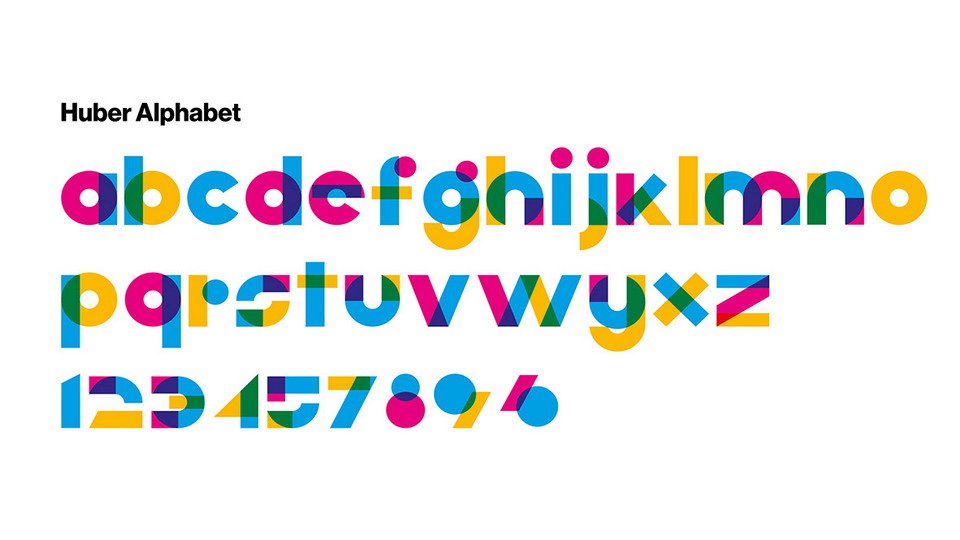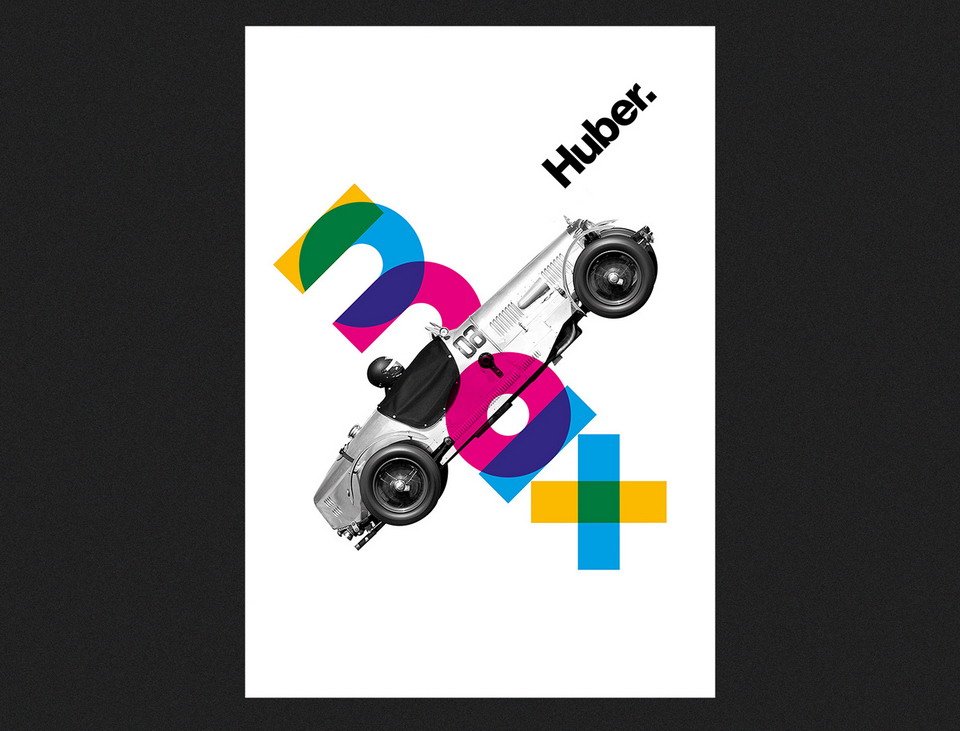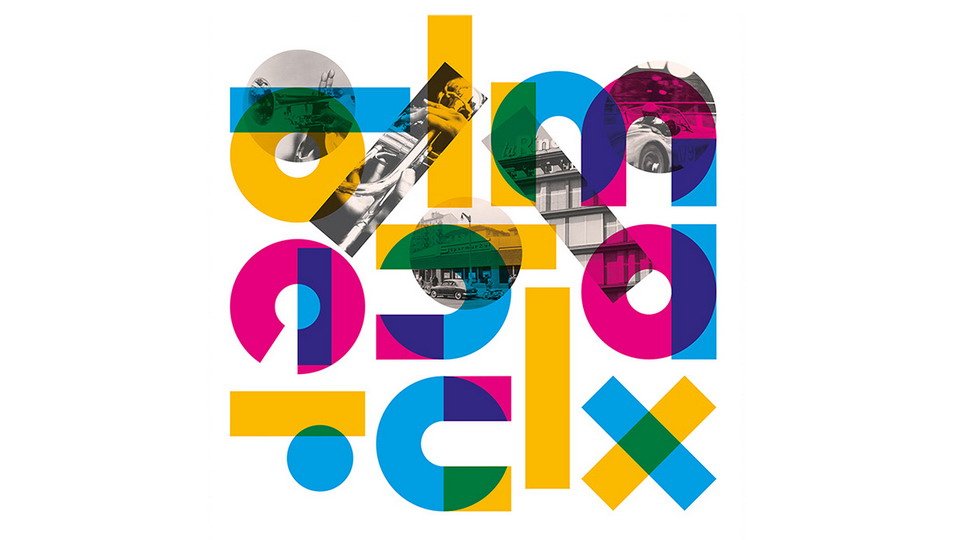
Huber Alphabet è il font realizzato dallo studio K95 in occasione del centenario della nascita di Max Huber, uno dei più grandi designer grafici del ‘900.
Nel font i ragazzi dello studio K95, Danilo De Marco e Dario Leonardi, hanno cercato di sintetizzare in un semplice alfabeto lo stile grafico e artistico di Huber.
Chi era Max Huber
Max Huber nasce a Baar, in Svizzera, il 5 Giugno del 1919, ma la sua attività artistica si svolse principalmente in Italia. Arrivò a Milano nel 1940, nello studio di Antonio Boggeri, che lo assunse dopo aver visto un suo biglietto da visita. Questo sembrava stampato tant’era preciso e impeccabile, ma in realtà era fatto a mano.
Antonio Boggeri stesso lo definì un grande sperimentatore, il ragno capace di infrangere la ragnatela.
Nel 1954 fu premiato con il Compasso D’Oro. Partecipò al movimento Arte Concreta insieme Munari, Dorfles, Monnet e Soldati. Nel corso della sua carriera fu autore di moltissime identità visive, come la Rinascente, la Triennale di Milano, Coin, Esselunga, di copertine, come quelle realizzate per Einaudi. Ma anche di manifesti, come quelli realizzati per Borsalino, Pirelli e la Rinascente, e di allestimenti per la Rai, per l’Eni e per Montecatini.
Lo studio K95
Danilo De Marco è uno dei fondatori dello studio K95 di Catania ed è proprio lui ad aver avuto l’idea di omaggiare Max Huber con un font speciale, proprio in occasione del centenario della sua nascita.
“Quando iniziai i miei studi accademici e conobbi Huber attraverso i libri, rimasi colpito e affascinato dal suo modo di fare grafica. Pur essendo un grafico di formazione svizzera riuscì a rompere gli schemi, ad andare oltre l’utilizzo classico della griglia”.
Ed insieme a De Marco, compagno nello studio e nella realizzazione del font troviamo Dario Leonardi. Insieme hanno provato a ricordare Huber sintetizzando il suo stile e la sua arte in un font vettoriale: l’Huber Alphabet.
L’Huber Alphabet
È così che nasce questo font, che come racconto gli stessi ideatori è “un’alfabeto nato dalla forte ispirazione che abbiamo avuto osservando tutto ciò che egli ha creato. È un alfabeto geometrico, che ricorda vagamente quello di Herbert Bayer all’interno del Bauhaus. Vuol essere un richiamo al passato, ma anche al presente. L’alfabeto è colorato simulando la tecnica di sovrastampa che Huber utilizzò in molti dei suoi lavori e che divenne un po’ il suo marchio di fabbrica”.
Lo studio K95 ha poi utilizzato le grandi passioni dell’artista per promuovere il font, realizzando appositi poster. Huber era, infatti, appassionato di gare automobilistiche, di sci, di musica jazz.